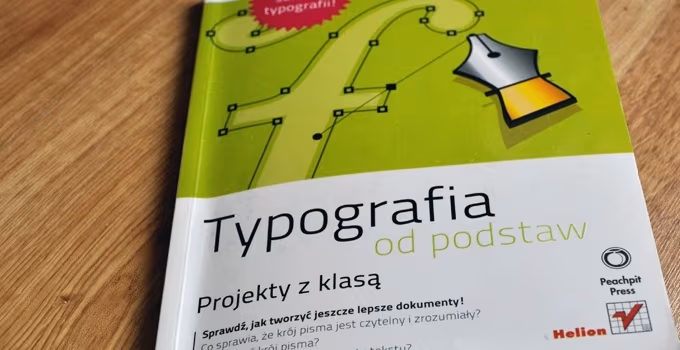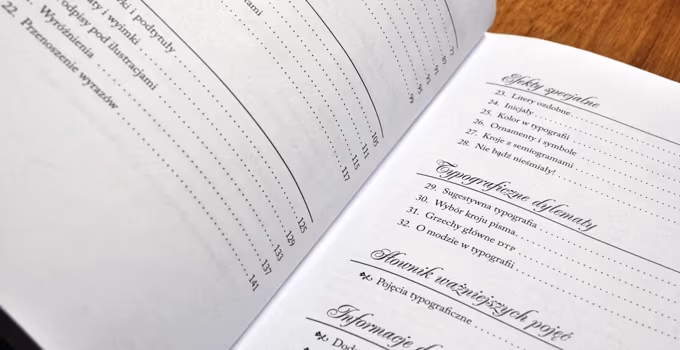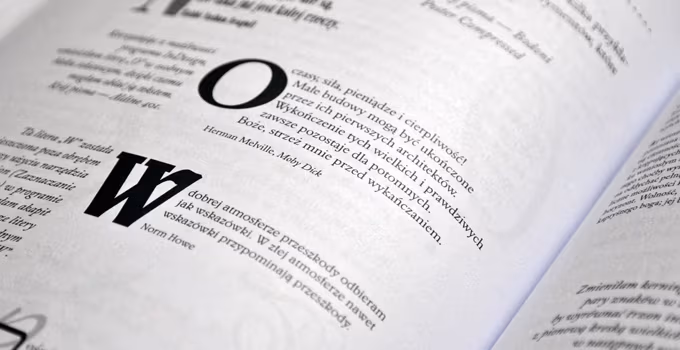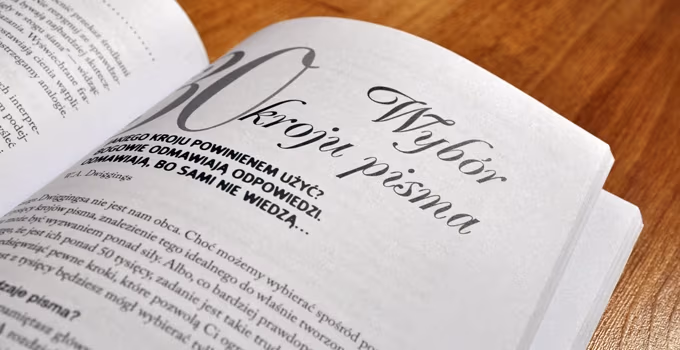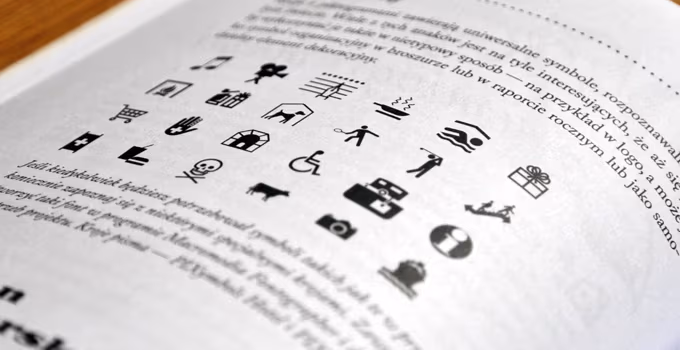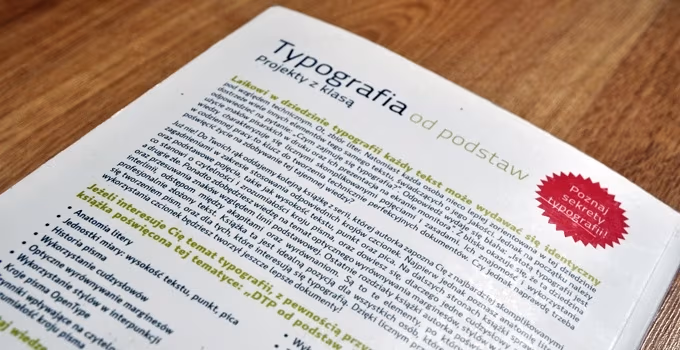
Czytanie książek branżowych to dobry sposób na dość efektywne poszerzanie swojej wiedzy. Dzięki temu można nie tylko dowiedzieć się więcej na temat interesującej nas dziedziny, ale także poznać nowych twórców, ich sposób myślenia i działania. Czytanie książek, poszerza także nasz zakres słownictwa, co na pewno pomaga w przyszłych kontaktach z klientami. Morał jest z tego taki, że czytać warto… wszystko i zawsze.
Jak już ustaliliśmy – czytanie przynosi same korzyści, kolejne pytanie, na które odpowiedzieć jest już trudniej brzmi… Co czytać? W tej serii artykułów, które będą raczej recenzjami przeczytanych przeze mnie książek, postaram się Wam pomóc w wyborze odpowiedniej dla Was literatury.
O książce Typografia od podstaw. Projekty z klasą dowiedziałam się czytając jeden z tematów na moim forum graficznym. Tytuł brzmiał zachęcająco, a ja trochę przytłoczona książką Elementarz stylu w typografii Roberta Bringhurst-a chciałam zasmakować czegoś lżejszego. Długo nie zwlekając zamówiłam tą książkę, oraz jej bliźniacze wydanie – DTP od podstaw. Projekty z klasą tej samej autorki.
Pierwsze wrażenie
Książka Robin Willians już na pierwszy rzut oka sprawia wrażenie wydania lekkiego – zarówno w sensie przekazu, jak i faktycznej wagi. Zdecydowanym jej plusem, szczególnie dla dziewczyny, jest jej mała waga, a co za tym idzie – możliwość bezproblemowego noszenia jej w torebce. Wiem, że dla niektórych może to brzmieć płytko, ale mężczyzno – noś codziennie na ramieniu 5kg, to porozmawiamy.
Okładka książki „Typografia od podstaw. Projekty z klasą” autorstwa Robin Williams
Przechodząc dalej… okładka książki jest estetyczna, jednak nie zachwyca. Przeglądając książkę przez cały czas odnoszę podobne wrażenie. Porównując to wydanie do wydania Elementarzu… ma się wrażenie, że obie książki nie mają wiele wspólnego od strony wydawniczej.
Moim zdaniem – książka ucząca zasad typografii i mówiąca o wszystkich jej wartościach estetycznych, wzmacnianiu przez nią przekazu, powinna sprawiać inne wrażenie. Użyte fonty, jakość papieru i rozkład treści pozwalają myśleć, że mamy do czynienia raczej z wydaniem niskobudżetowym (cena książki to w końcu 37zł).
Czego dowiemy się z książki?
Typografia od podstaw podzielona jest na dziesięć rozdziałów dotykających różnych tematów. Są to po kolei: Krótka historia pisma, Czytelność  i zrozumiałość, Interpunkcja, Mistrzowski skład, Odstępy, Szczegóły, Efekty specjalne, Typograficzne dylematy, Słownik ważniejszych pojęć oraz Informacje dodatkowe.
Po przebrnięciu przez spis treści natrafiamy na wstęp. Autorka w dość ciekawy sposób wprowadza czytelnika w świat książki. Pokazuje na przykładach podstawowe błędne i poprawne projekty w celu zachęcenia czytelnika do zgłębienia się w tę tematykę. Tłumaczy anatomię litery i wyjaśnia pojęcia, które wykorzystywane będą w książce. To bardzo dobry pomysł, szczególnie dla osób rozpoczynających swoją przygodę z typografią. Wskoczenie na głęboką wodę mogłoby być dla nich dość traumatyczne (dla mnie było, kiedy czytałam Elementarz stylu w typografii).
Krótka historii pisma
To zdecydowanie krótki rozdział. Poznajemy w nim podstawowy podział krojów pisma i dowiadujemy się czym się charakteryzują. Oprócz opisu dla każdej z kategorii autorka przedstawia nam przykłady opatrzone komentarzem, który pokazuje charakterystyczne elementy fontów tego rodzaju.
Czytelność i zrozumiałość
W tym rozdziale autorka zapoznaje nas z takimi zagadnieniami jak kroje bezszeryfowe i szeryfowe, majuskuły i minuskuły, odstępy międzyliterowe i międzywyrazowe czy interlinia. Są to pojęcia, które powinny być ważne dla każdego, kto chce dbać o typografię w swoich projektach.
Na uwagę w tym rozdziale zasługuje także poddział Długość wiersza, a wyrównanie, gdzie autorka dając kilka prostych rad uczy nas jak dobrać optymalną wielkość fontu lub szerokość wiersza. Początkowo takie matematyczne podejście do tego tematu może okazać się zbędne, jednak jeśli chcecie dbać o maksymalny komfort czytania w złożonych przez Was tekstach, powinniście wziąć to pod uwagę.
Interpunkcja
Interpunkcja to zagadnienie wałkowane w szkołach w Polsce od podstawówki. W sporej większości… bezskutecznie. Zasady wymieniane w książce dotyczą poprawnego stawiania znaków cudzysłowów, apostrofów, minut, sekund. Oprócz tego autorka wspomina o odpowiednim korzystaniu z nawiasów, czy łączników (z którymi, swoją drogą, sama mam problem).
Oprócz typowych zagadnień związanych z korzystaniem ze znaków interpunkcyjnych, w tym rozdziale możemy dowiedzieć się co zrobić, aby znaki z których korzystamy były nie tylko poprawnie wstawione, ale też prezentowały się efektownie.
Mistrzowski skład
Ten rozdział poświęcony jest typograficznym możliwościom fontów zgodnych ze standardem Open Type. Autorka pokazuje tutaj możliwości jakie można osiągnąć posiadając prawdziwe kapitaliki, znaki zwężone i rozszerzone, czy cyfry nautyczne. Oprócz suchych informacji na temat tego co oznaczają poszczególne pojęcia, w tym rozdziale dowiadujemy się jak odpowiednio dopasować daną odmianę fontu do aktualnych potrzeb.